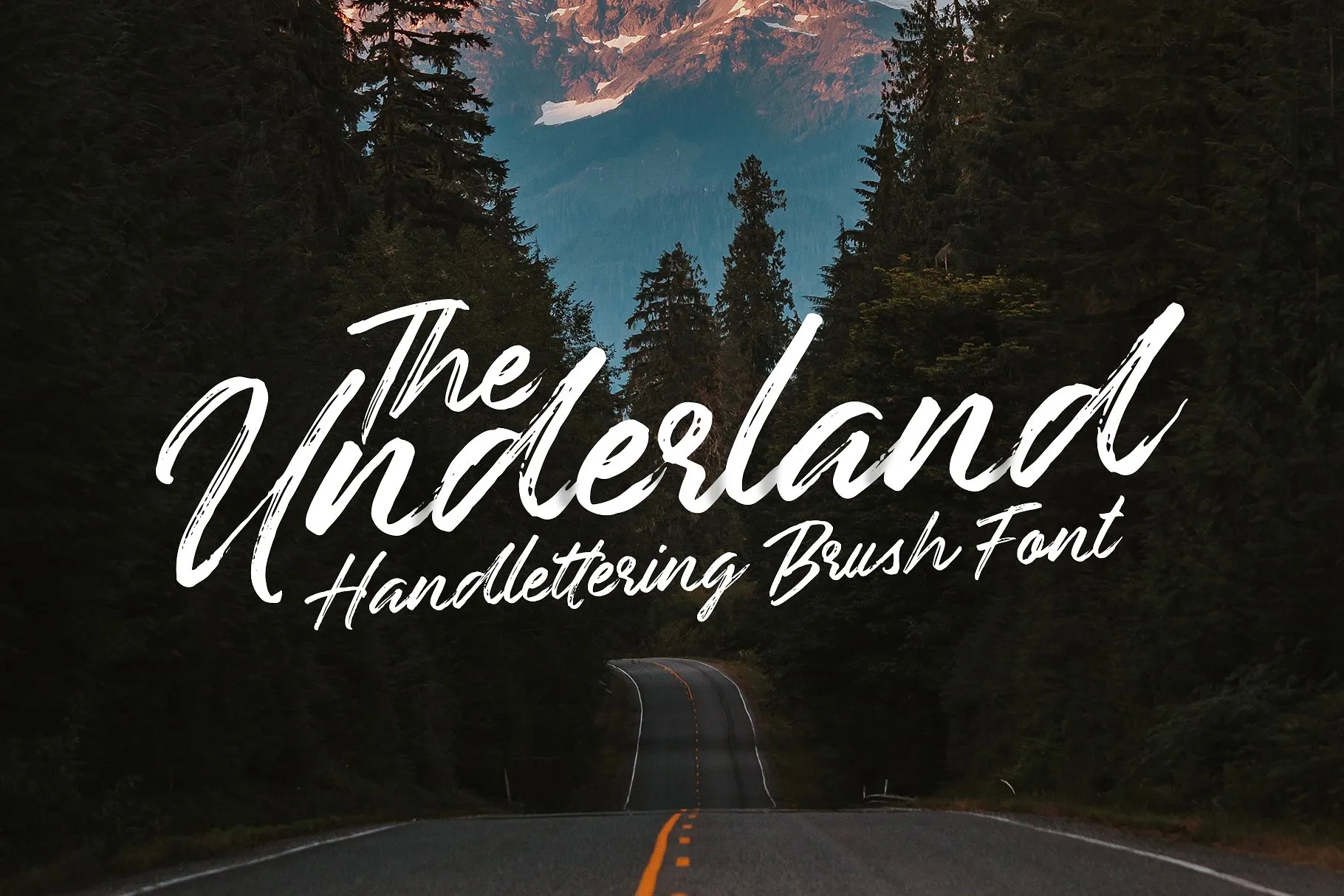
Aqui está uma descrição envolvente e natural para a página de download da font ‘Underland Script Font’: Descubra ‘Underland’, uma nova adição à família de fontes 1001fonts. Inspirada na arte do desenho à mão livre, esta brush script é perfeita para projetos criativos. Com seu estilo clássico e movimento dramático, a Underland é uma opção ideal para assinaturas, cartões de visita, embalagens de produto, logotipos, posters e até mesmo desenhos de roupas. Seja você um designer gráfico ou uma artesã que busca dar um toque único aos seus projetos impressos, Underland é a fonte perfeita para criar experiências memoráveis. Transforme sua paleta de ferramentas com esta beleza única e versátil.